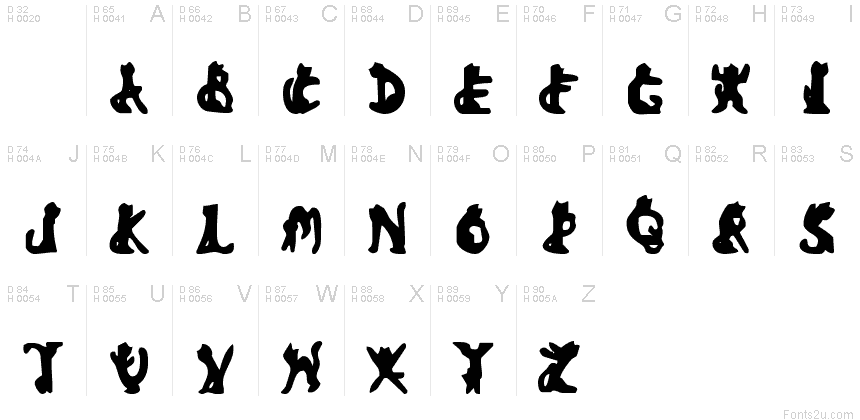
Bad Black Cat autorstwa Heather Daniels to darmowy krój typu trash script, który zmienia każde słowo w szereg skradających się, atramentowych sylwetek kotów. Litery są wyraziste, nieregularne i nieco psotne, o masywnych kształtach, które wyglądają, jakby wycięto je ręcznie i rozchlapano na stronie. Całość ma zadziorny, halloweenowy klimat, przypominający upiorny plakat nabazgrany o północy.
Dzięki Bad Black Cat natychmiast nadasz charakteru ulotkom na imprezę halloweenową, przerażającym zaproszeniom, szyldom nawiedzonych domów, horrorom, torbom na słodycze i okolicznościowym postom w mediach społecznościowych. Ten darmowy font najlepiej sprawdza się w dużym rozmiarze, pozwalając w pełni wyeksponować kocie kształty i surowe krawędzie. W tekstach głównych zestaw go z prostym, wąskim krojem bezszeryfowym, aby dzikie, czarownicze nagłówki pozostały w centrum uwagi.